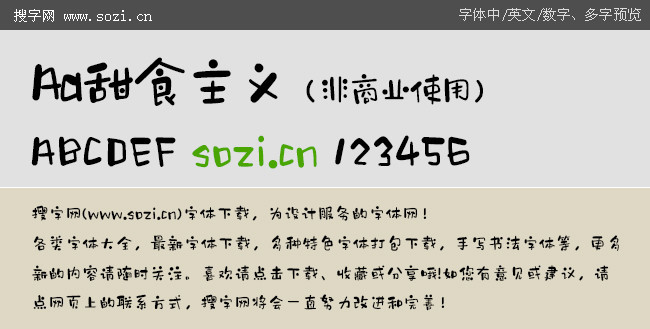
Aa甜食主義
搜字網(wǎng)給大家提供一款A(yù)a甜食主義(非商業(yè)使用)中文字體下載,該字體是一款一款非常可愛的藝術(shù)字體,這款字體筆觸圓潤可愛,字形卡通可愛,給人一種非常有趣的視覺感受,適用于平面宣傳設(shè)計、網(wǎng)頁設(shè)計、海報設(shè)計等應(yīng)用(此字體為個人非商用版,商用可以聯(lián)系QQ:1006760504)。